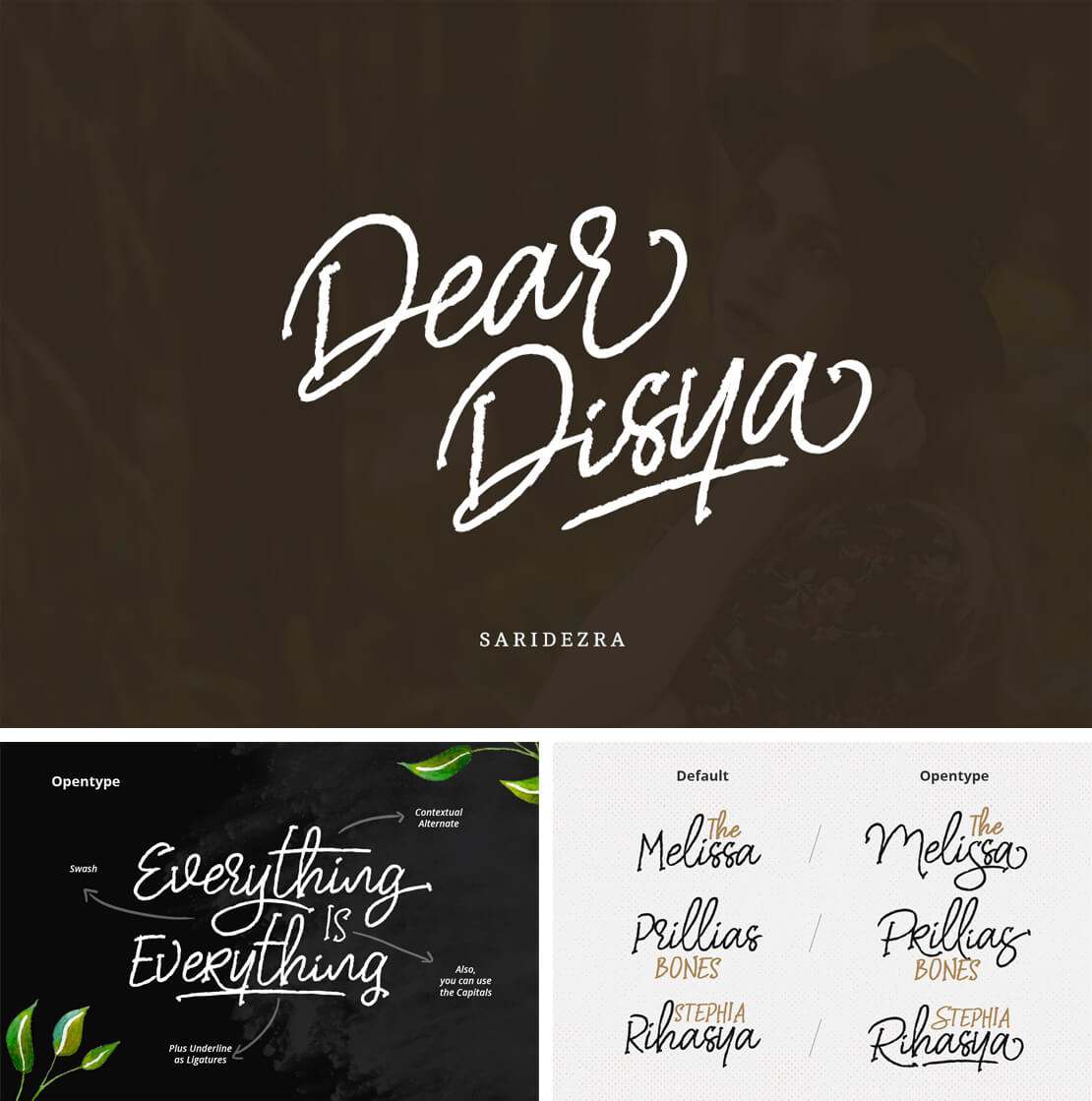
Dear Disya
»Dear Disya« bietet eine natürliche, leicht schwungvolle Handschrift-Ästhetik. Die Schriftart kann kostenlos im Opentype- und TTF-Format heruntergeladen werden.
Neben vielen Ligaturen und zusätzlichen Zeichen unterstützt die Schriftart auch deutschsprachige Umlaute.